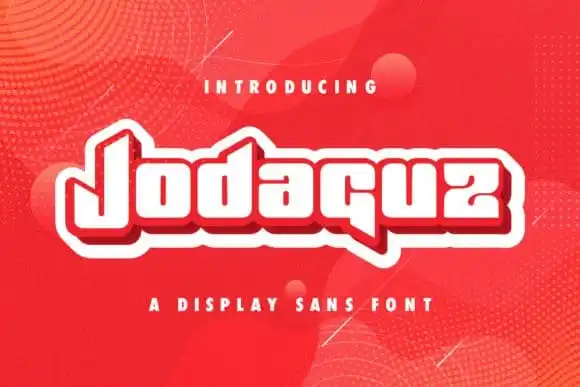
Jodaguz Display Font – Download Grátis
A Jodaguz Display Font é uma escolha excepcional para qualquer projeto que busque um visual atemporal e moderno. Desenvolvida pelo StringLabs, esta elegante tipografia tem uma aparência marcada por sua bold e retro estilo, se destacando em ambientes variados. Perfeita tanto para uso em fundos coloridos quanto como título de destaque único, ela dá um update contemporâneo a qualquer projeto de design que você esteja criando. Além disso, sua sensação tecnológica faz dela uma excelente opção para títulos, subtítulos e interfaces de usuário. Ideal tanto para designers iniciantes quanto profissionais experientes, Jodaguz Display é uma fonte display perfeita para aqueles buscando uma aparição inovadora em qualquer projeto visual.